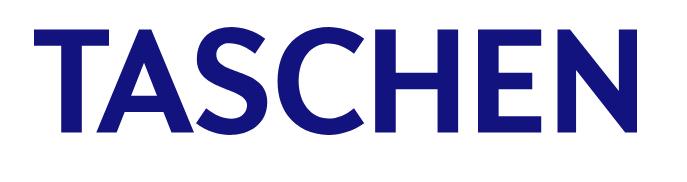
Suche Schrift des TASCHEN-Logos
Sieht mir nach einer "Trade gothic" aus, aber das "C" scheint mir umgebastelt oder aus einer anderen Schrift, weil sich im Gegensatz zum "S" die Strichstärke verändert.
Rosemary Samuels SemiBold und
Texta Narrow Heavy
kommen dem Ergebnis aber schon nahe.